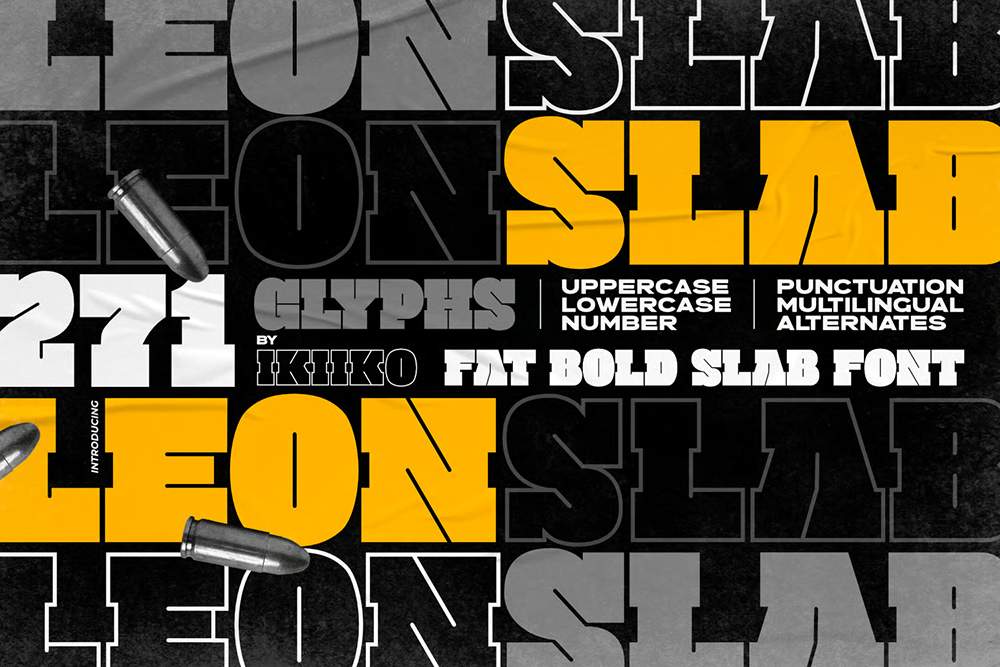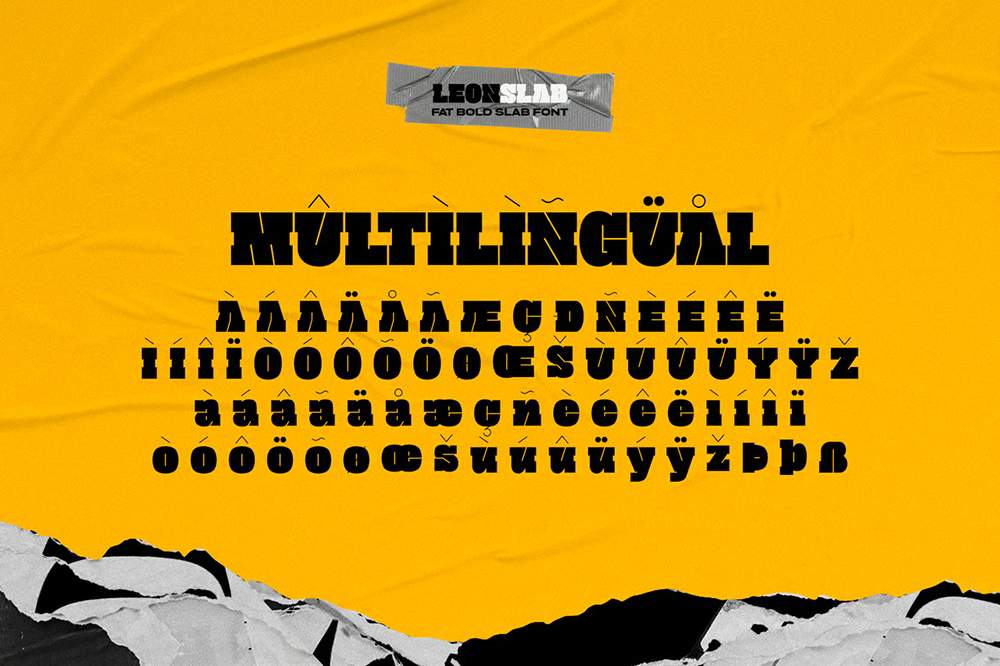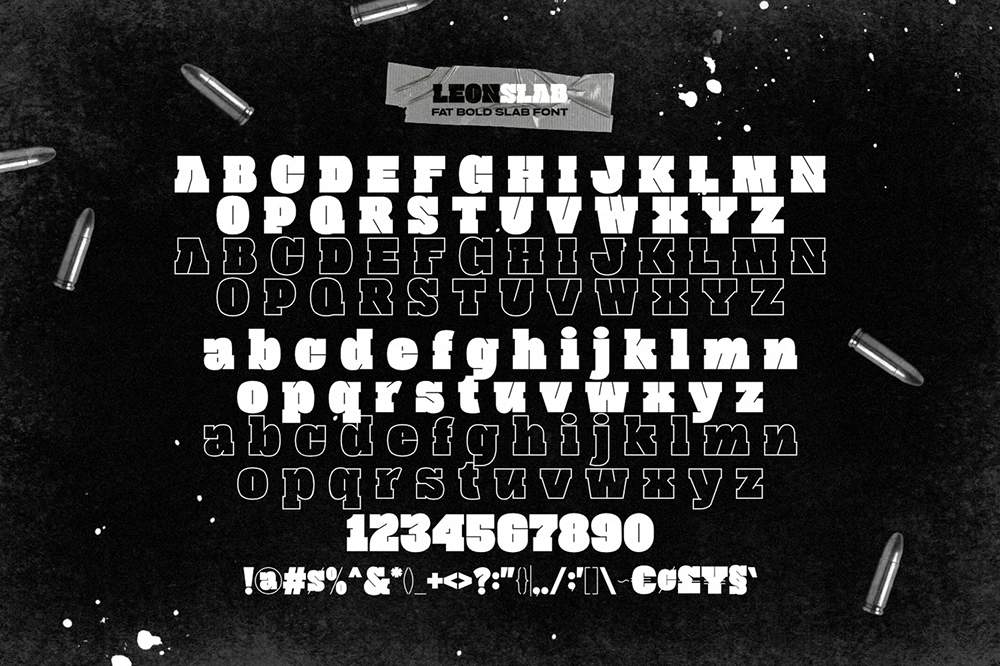
فونت پرمیوم و انگلیسی Leon Slab Font فونتی قوی و مسلط که قدرت و اعتماد به نفس را ساطع میکند. حروف فونت Leon Slab با مهارت و با خطوط پهن و محکم ساخته شدهاند که به آنها حضور قابل توجهی در صفحه يا مانيتور میدهد. هر کاراکتر دارای تهاجمی جذاب است که آن را برای عناوين، سرتيترها و تابلوهايی که در آنها تأثيرگذاری مهم است، ايدهآل میکند.
Leon Slab سبک منحصر به فرد دارد – پررنگ و مشخص – تا نيازهای مختلف طراحی را برآورده کند و باعث میشود متن در مقابل پسزمينه برجسته شود و حسی پويا به آن میبخشد.
اين فونت برای ايجاد پوستر فيلم، عنوان فيلم، پوستر، عنوان، جلد، طرح مجله، بستهبندی مواد غذايی و آشاميدنی، نقل قولها يا به سادگی به عنوان يک پوشش متن شيک برای هر تصوير پسزمينه بسيار مناسب است.
مزایای استفاده از فونت لاتین Leon Slab چیست؟